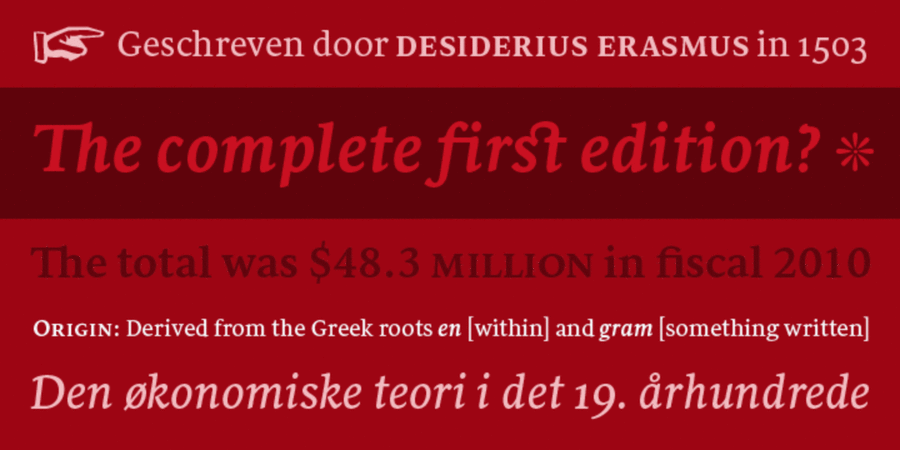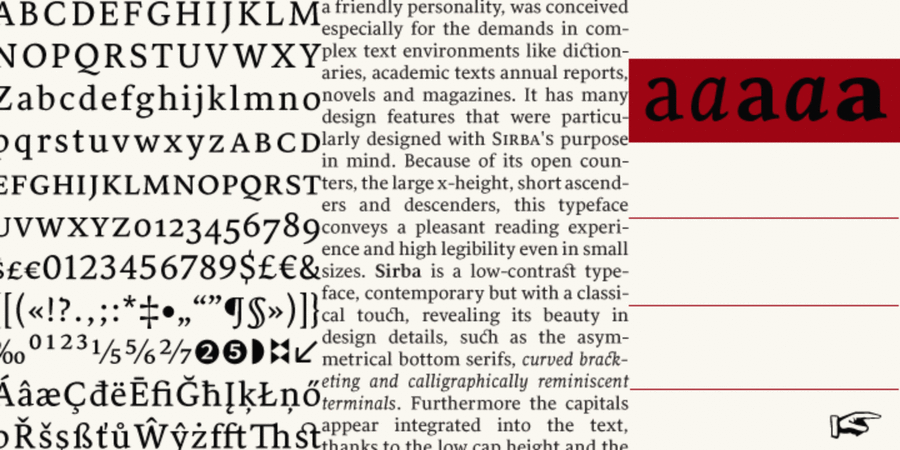
Опис гарнітури Sirba CYRШрифт Sirba, старостильна антиква з доброзичливою індивідуальністю, був задуманий спеціально для роботи у складних текстових середовищах, як словники, академічні тексти, щорічні звіти, книги та журнали. Він має безліч конструктивних особливостей, які були спеціально розроблені з урахуванням цілей шрифту. Завдяки відкритій апертурі, великій висоті рядкових, коротким виносним елементам, цей шрифт забезпечує комфортне читання і високу розбірливість навіть у невеликих розмірах. Sirba – це низькоконтрастний шрифт, сучасний, але з класичним рисунком, що розкриває свою красу в дрібних деталях, таких як асиметричні зарубки та каліграфічні термінали. Також шрифт містить капітель, табличні цифри, що робить цей шрифт дуже корисним для річних звітів і таблиць. Sirba доступний у чотирьох класичних накресленнях, плюс спеціальна Наджирна версія. Її особливість у тому, що її пропорції сконструйовані таким чином, щоб внутрішній просвіт літер залишався досить великим. Це означає, що Sirba Black ширший від багатьох текстових шрифтів аналогічної насиченості, що забезпечує чудову читабельність. Під час проектування шрифтового сімейства велика увага приділялася курсивам. Курсив досить просто виділяється при читанні, але не створює плям при перегляді тексту в цілому. Набір символів Sirba CYR охоплює більше 80 мов на латиниці, кирилиці, плюс політонічна грецька абетка. Шрифт також включає безліч типографічних тонкощів, як набір стрілок, рідкісних лігатур, капітель, 5 наборів цифр і багато іншого. Інтенсивне вивчення дрібнокегельних шрифтів періоду металевого складання, що викиристовувались у бібліях і словниках, та розуміння «секретів» класичної типографіки, сильно вплинуло на дизайн Sirba. Шрифт розробив Нікольєн ван дер Кьор у 2010 році.
Асоціації з сімейством шрифтів Sirba CYRОсобистість і характер гарнітури:
комільфо, благородний, консервативний, традиційний, класичний, пафосний, художній, сріблястий, освічений, майстерний, архітектурний, аристократичний, елітний, якісний, історичний, гуманітарний, срібний, динамічний, дорогий, розумний, приємний, комфортний, культурний, гармонійний, спокійний, ввічливий, витончений, красивий, акуратний, поважний, старанний, тактичний, зразковий, сильний, переконливий, авторитетний, важливий, впевнений, стійкий, серйозний, міцний, точний
бібліотека, мистецтво, музей, література, естетика, проза, поезія, музика, архітектура, геральдика, чай, вино, освіта, срібло, комільфо, історія, замок, концерт, пейзаж, філософія, симфонія, квіти, карти, пам'ятник, меморіал, банкнота, монета, цінні папери, обід, вечеря, алкоголь, коньяк, Трофей, нагорода, прапор Гарнітура асоціюється з віком: